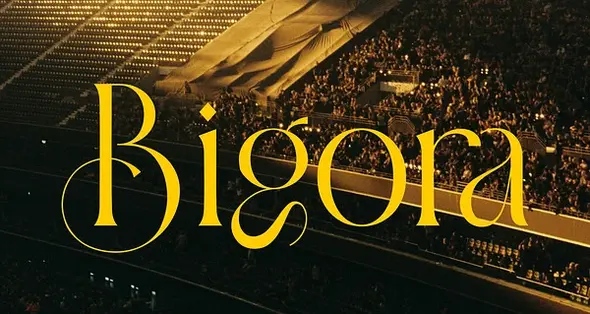
• Bigora || Modern Classy Serif Font, A Serif Font By Ermedia Studio
• circle سبک قلم: Serif
• circle حروف کوچک
• circle حروف بزرگ
• circle علائم نگارشی
• circle لیگچر
«بیگورا سریف» یک تایپ‌فیس مدرن و باکلاس برای تمامی طراحی‌های برندینگ و لوگو است. این فونت سریف دارای کاراکتری بسیار زیباست و برای طراحی کارت‌های دعوت، لوگوهای جذاب، عنوان فیلم‌ها، کارت ویزیت، عنوان کتاب و نام برند کاملاً مناسب است. بیگورا یک فونت سریف نرم است که حس پیچیدگی و به‌روز بودن را القا می‌کند. لیگاتورهای شیک این فونت، آن را به شریکی عالی برای هر پروژه‌ای تبدیل کرده است که در تمامی سبک‌های طراحی می‌نشیند.
• دارای لیگاتورهای زیبا (Ligature)
• شامل حروف بزرگ، حروف کوچک، اعداد و علائم نگارشی
Bigora Serif is a modern and classy font type for all branding and logo designs. This modern and classy Serif font has a beautiful character. This font is suitable for invitation card designs, cool logos, movie titles, movie names, business cards, book titles, brand names, and various other designs. Bigora Serif is a smooth serif font that exudes sophistication and the moment. Its stylish ligatures make this font a perfect partner for any project.
- Ligature
- Uppercase and lowercase
- Numbering and Punctuation